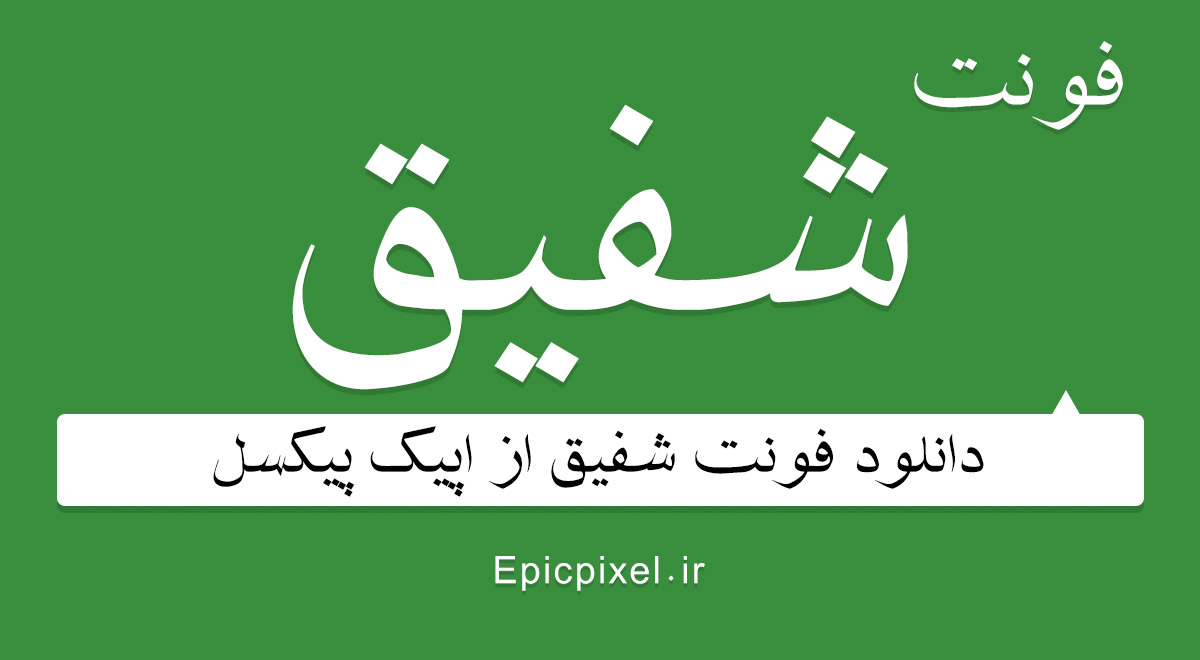
انتخاب فونت مناسب، نقشی حیاتی در جذابیت و اثربخشی طراحی ایفا می کند. در میان گستره وسیع فونت های فارسی، “فونت شفیق” به عنوان گزینه ای قابل توجه مطرح می شود. جالب توجه است که “فونت شفیق” الهام بخش طراحی “فونت پیکان” بوده است. این در حالی است که “فونت پیکان” معمولاً یک فونت تجاری محسوب می شود ، در حالی که “فونت شفیق” اغلب به صورت رایگان در دسترس قرار دارد. این موضوع می تواند یک مزیت کلیدی برای استفاده از “فونت شفیق” به شمار آید، زیرا طراحان می توانند به زیبایی شناسی مشابه دست یابند بدون نیاز به پرداخت هزینه.
در بررسی ویژگی های “فونت شفیق”، مشخص می شود که این فونت، یک فونت فارسی ، عربی است. اگرچه طراح اصلی آن به طور دقیق مشخص نیست، اما در گذشته توسط ابوالفضل سيل سپور و مجتبی کیا ویرایش و اصلاح شده است. این ماهیت فارسی ، عربی، دامنه کاربرد آن را گسترش می دهد و امکان استفاده در پروژه هایی را فراهم می کند که نیازمند پشتیبانی از هر دو زبان هستند. این تنوع زبانی، یک امتیاز مهم برای طراحان محسوب می شود. اطلاعات فنی نشان می دهد که این فونت معمولاً در فرمت های TTF و گاهی OTF ارائه می شود. در دسترس بودن در فرمت TTF، سازگاری آن را با طیف وسیعی از سیستم عامل ها (ویندوز و مک) و نرم افزارهای طراحی تضمین می کند.
این سازگاری گسترده، استفاده از آن را برای اکثر طراحان آسان می سازد. با توجه به اینکه “فونت پیکان” با الهام از “فونت شفیق” طراحی شده و توصیفاتی نظیر جسور، جدی و تأثیرپذیرفته از خط نسخ برای آن ذکر شده است ، می توان حدس زد که “فونت شفیق” نیز دارای ویژگی های مشابهی باشد. این امر می تواند برای کاربرانی که به دنبال چنین سبک بصری هستند، جذاب باشد. همچنین، برخی منابع به نسخه ها یا استایل های مختلف “فونت شفیق” (مانند normal، Mangle، Outline، Shad و bold) اشاره کرده اند. این تنوع در استایل می تواند جذابیت این فونت را برای طراحان با نیازهای گوناگون افزایش دهد.
دانلود“فونت شفیق” به دلیل ویژگی هایش، کاربردهای متنوعی در طراحی دارد. همانطور که در مورد “فونت پیکان” (که از آن الهام گرفته) گفته شده، این فونت احتمالاً برای نوشته های کوتاه، عناوین، برندهای مرتبط با مد و لوکس و حتی محصولات وارداتی به دلیل داشتن یک “لهجه” خاص، مناسب است. این کاربردها نشان می دهند که “فونت شفیق” می تواند در پروژه های مختلفی از جمله طراحی هویت بصری و مواد بازاریابی مورد استفاده قرار گیرد. علاوه بر این، برخی منابع به طور مستقیم اشاره کرده اند که از “فونت شفیق” می توان در نوشتن عناوین و تیترها، طراحی بنر، کارت ویزیت، لوگوتایپ و حتی متون طولانی استفاده کرد. این گستردگی کاربرد، “فونت شفیق” را به یک انتخاب منعطف برای نیازهای طراحی مختلف تبدیل می کند. همچنین، با توجه به الهام بخشی آن برای طراحی هایی مانند پوستر، جلد و کاور ، می توان دریافت که این فونت در پروژه های بصری چاپی و دیجیتالی نیز کاربرد دارد.